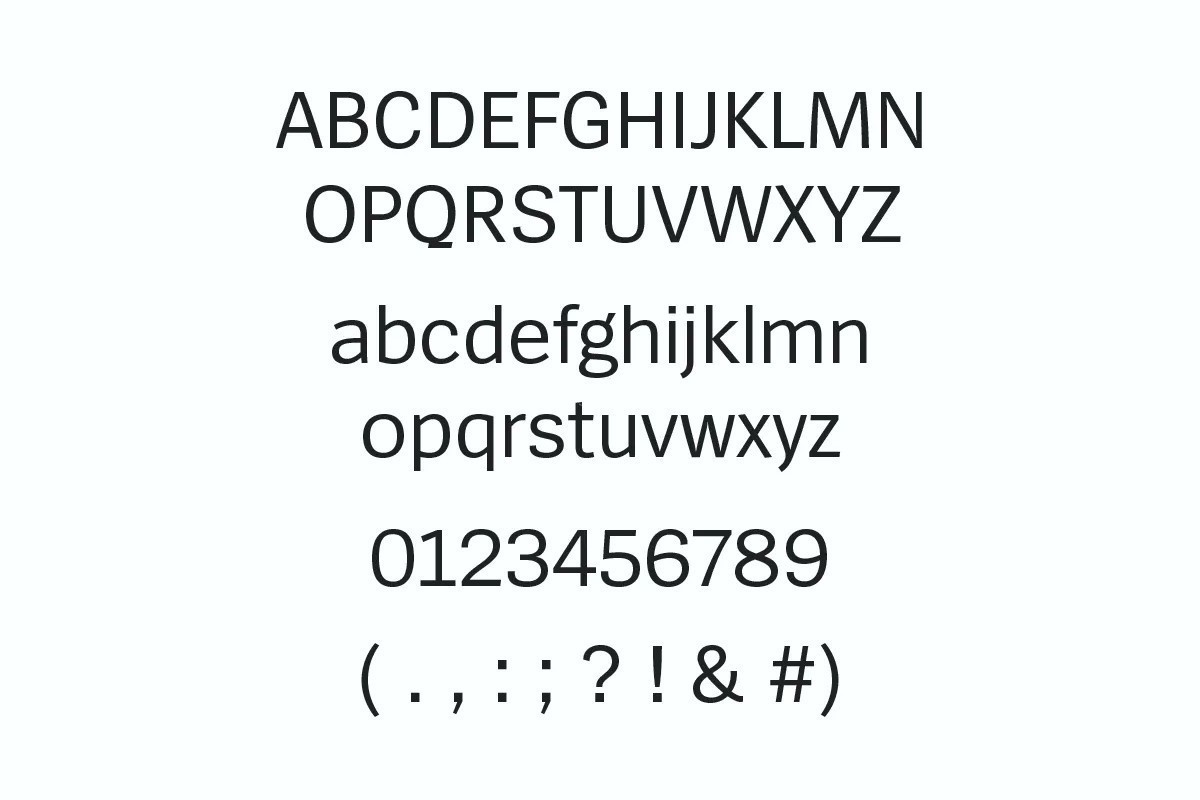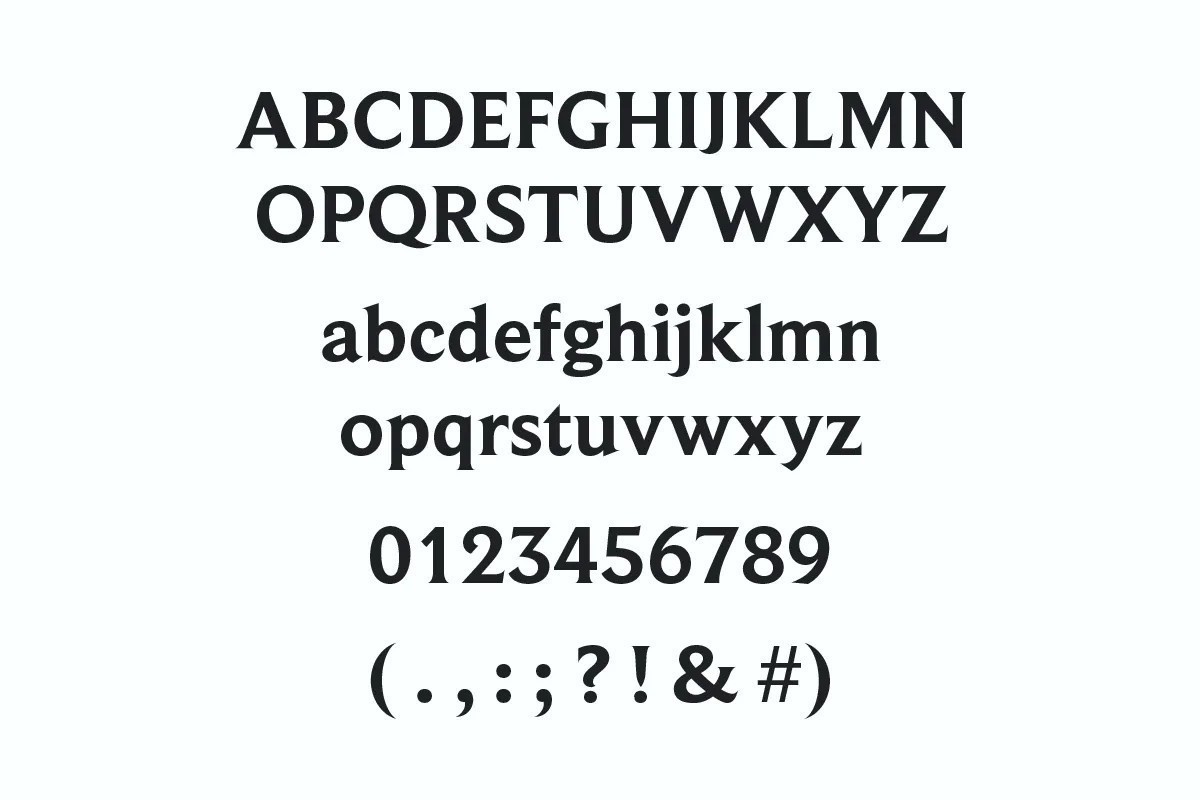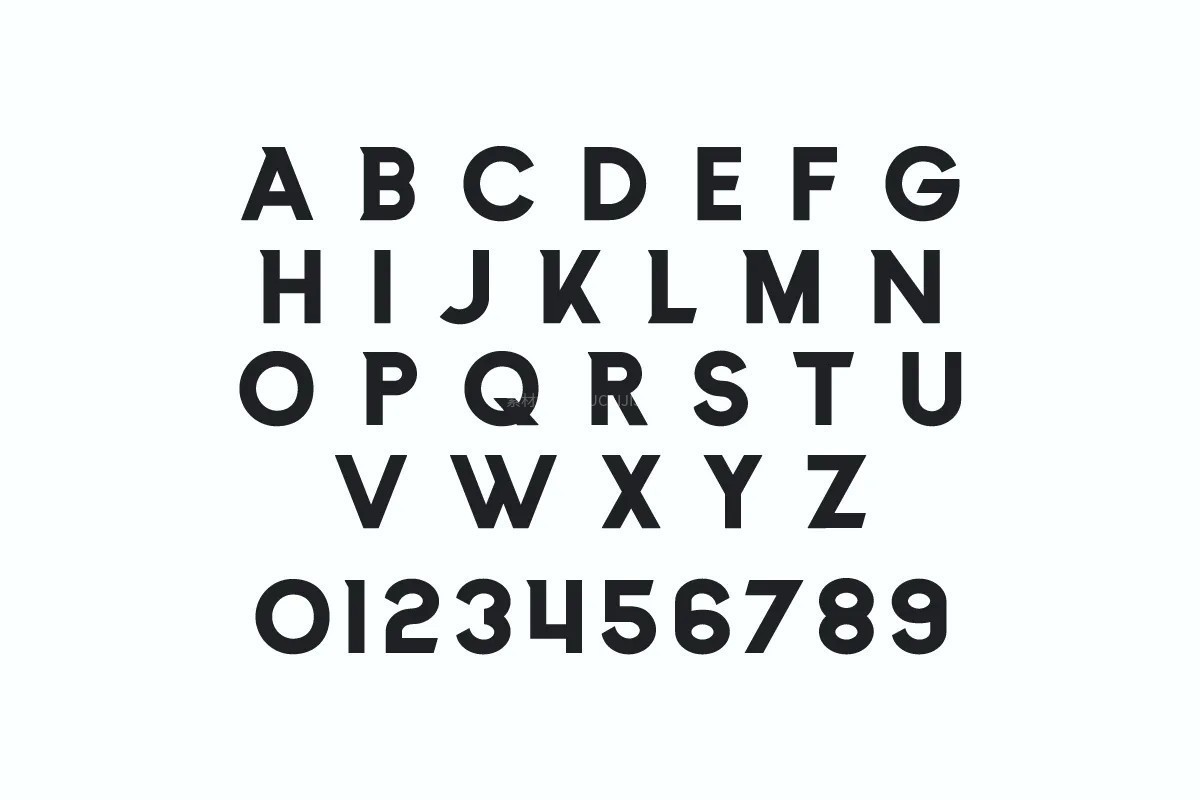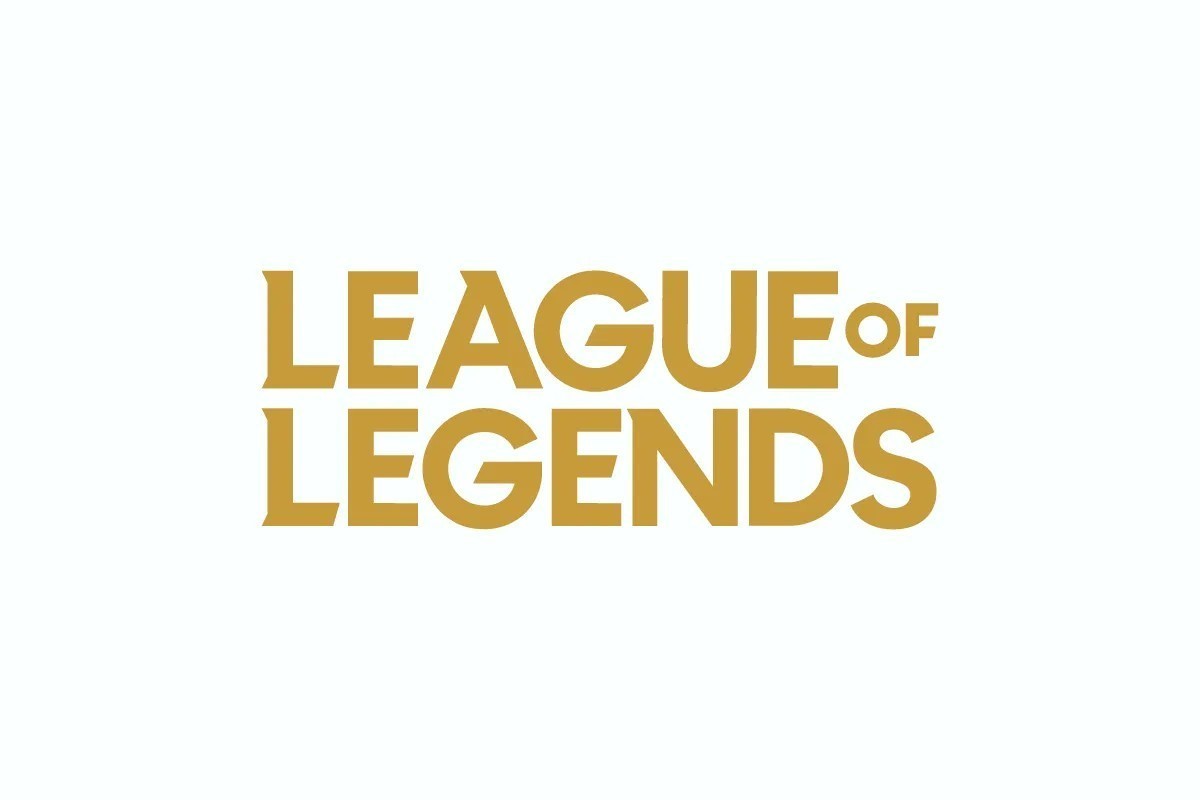
英雄联盟(LoL)全套视觉字体合集
《英雄联盟》(League of Legends)作为全球极具影响力的多人在线竞技游戏,构建了高度专业且辨识度极强的视觉识别系统。
英雄联盟(LoL)全套视觉字体合集
本资源深度解析并收录了该游戏标志及 UI 界面所使用的核心字体系列:包含完美复刻当前游戏 Logo 设计的“League”免费字体,及其早期经典灵感来源“Friz Quadrata”衬线字体;
英雄联盟(LoL)全套视觉字体合集
同时涵盖由 Lucas de Groot 设计、负责游戏内正文与大量文字信息清晰呈现的“Spiegel”字体;
英雄联盟(LoL)全套视觉字体合集
以及由 Monotype 专属定制、专为游戏标题、界面菜单及视觉强调而生的“Beaufort For LoL”字体(配备五种字重及斜体)。这套完备的字体组合完美平衡了信息阅读的舒适度与电竞视觉的冲击力,是游戏美术与排版设计的顶级参考资料。
英雄联盟(LoL)全套视觉字体合集